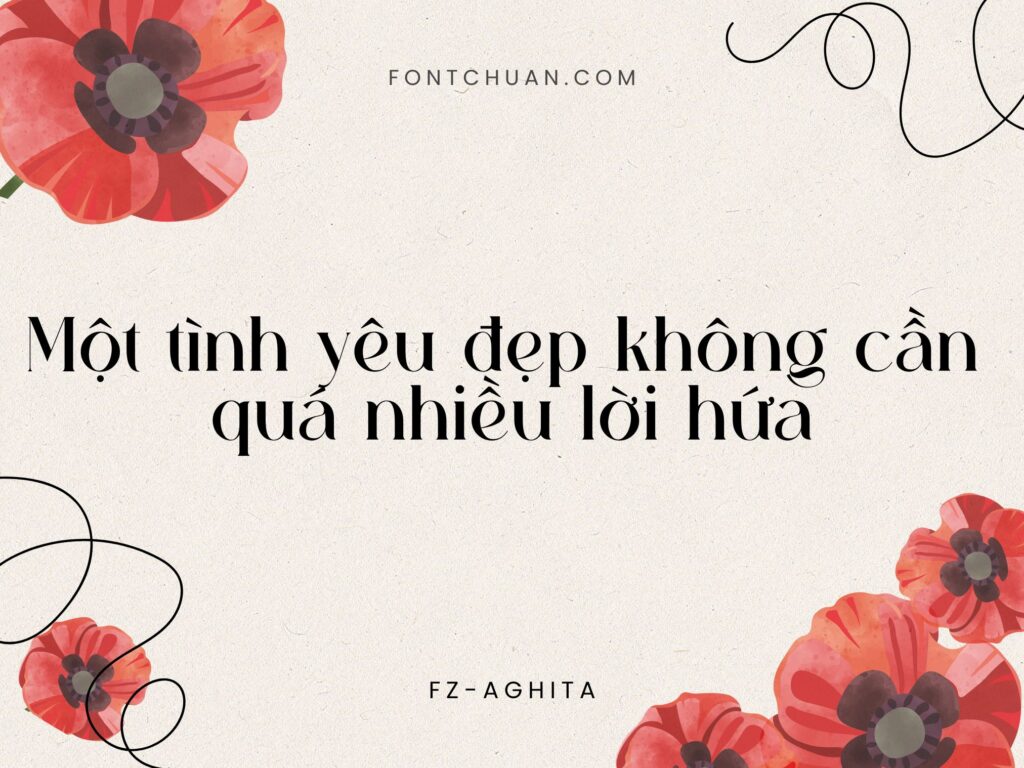
Font Fz-Aghita Việt Hóa
Fz Aghita là một phông chữ serif hiện đại, thanh lịch, được thiết kế bởi Tokopress. Phông chữ này mang đến vẻ đẹp tinh tế với các đường nét sắc sảo và tỷ lệ cân đối, giúp tạo điểm nhấn cho các thiết kế sang trọng. Phiên bản Fz Aghita đã được Việt hóa bởi Fonttiengviet, hỗ trợ đầy đủ các ký tự tiếng Việt, giúp người dùng dễ dàng ứng dụng vào các thiết kế mang bản sắc địa phương.
Về đặc điểm thiết kế, Fz Aghita sở hữu những đường cong mềm mại và các chân chữ sắc nét, tạo nên phong cách thanh lịch và trang nhã. Phông chữ này phù hợp cho các ứng dụng như thiết kế logo, tiêu đề, bìa sách, bao bì sản phẩm và các dự án sáng tạo khác. Đồng thời, Fz Aghita cũng có thể được sử dụng như một font chữ thiệp cưới, giúp các nhà thiết kế tạo ra những tấm thiệp sang trọng, tinh tế và lãng mạn. Về ngành nghề, Fz Aghita đặc biệt phù hợp với lĩnh vực quảng cáo, giáo dục, thiệp cưới và ảnh cưới.